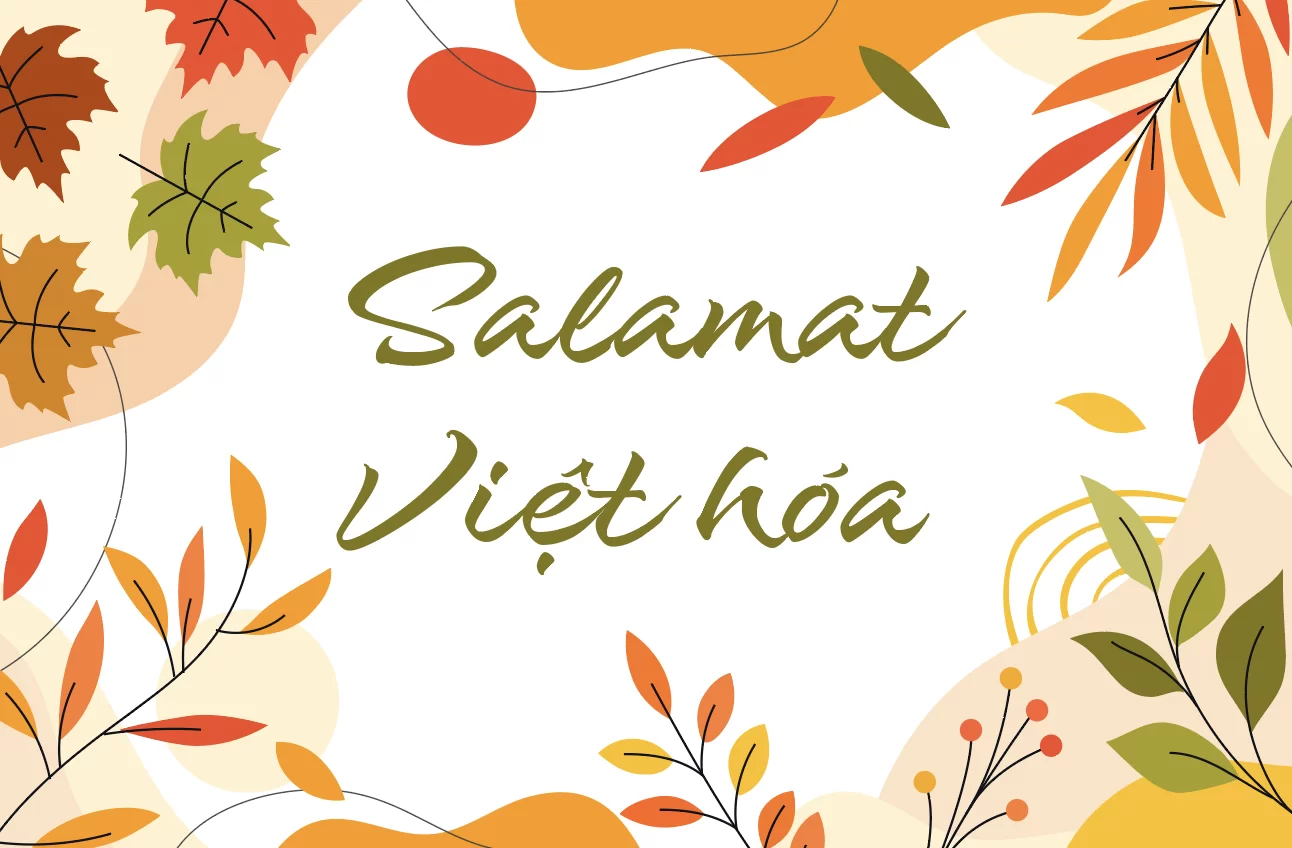
Salamat là một phông chữ mang phong cách thư pháp hiện đại với nét bút mềm mại, uốn lượn đầy duyên dáng. Font mang lại cảm giác gần gũi như những nét viết tay đầy tình cảm, rất thích hợp cho các thiết kế thiệp, thư mời, tiêu đề truyện tranh, hoặc các dự án sáng tạo cần yếu tố cá nhân hóa.
Bản Việt hóa được tinh chỉnh tỉ mỉ giúp hỗ trợ đầy đủ dấu tiếng Việt, giữ nguyên tinh thần nguyên bản của font với những nét gãy - nối mượt mà và hài hòa.